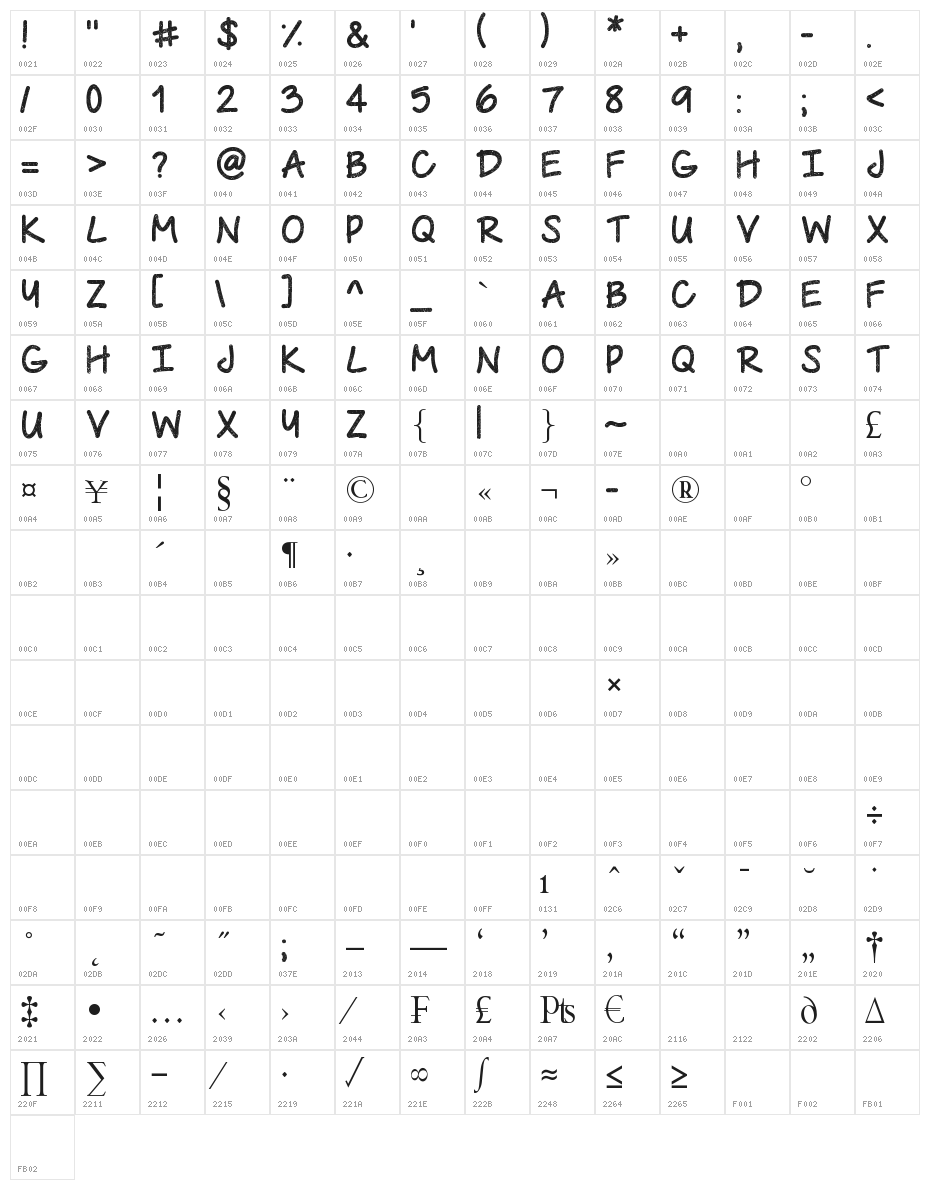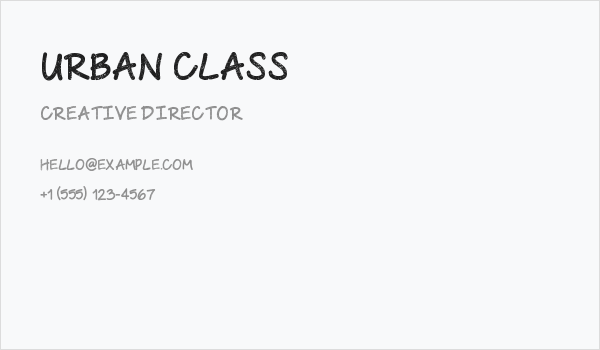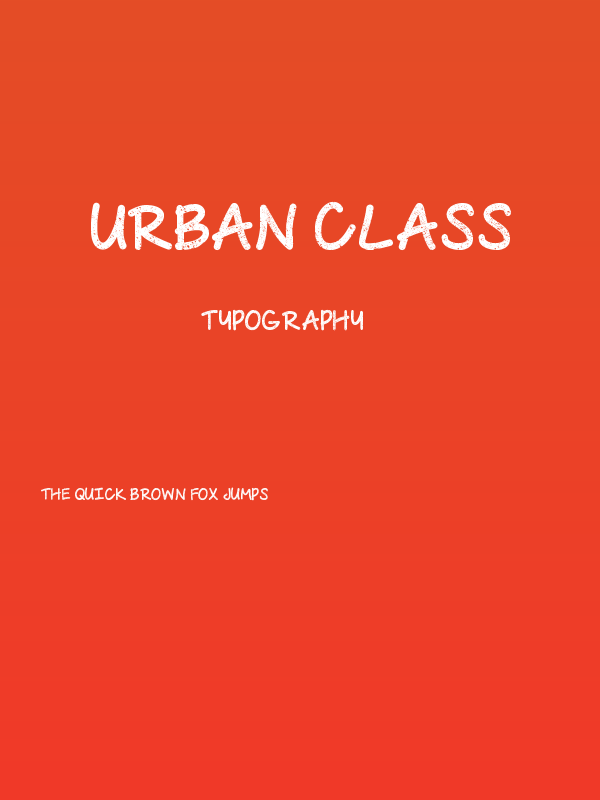
Urban Class Font
✎ Handwritten
| 整体风格 | Urban, Modern, Casual |
| 使用场景 | Logos, Posters, Branding |
| 推荐项目 | Ideal for streetwear branding, music album covers, graffiti art, and urban-themed posters. |